Es es sind mehr als zehn Jahre vergangen, bevor im Internet typografische Vielfalt Einzug hielt (siehe auch Heute ist Webfont-Tag, Fontblog-Beitrag vom 26. Feb 2010). Für mobile Anwendungen (Apps) darf es nicht noch einmal so lange dauern. Gerade die Verlagshäuser setzen auf textaffine Anwendungen, zum Beispiel eBooks, ePaper oder Zeitschriften-Apps. Mit mobilen Fonts und entsprechenden Lizenzen gibt es keinen Grund mehr, dass Bücher, Zeitschriften und Zeitung auf Mobilgeräten anders aussehen als die gedruckten Exemplare.
Um den Einstieg noch sicherer, einfacher und kostengünstiger zu gestalten, bringt FontFont als erstes Schriftenhaus 15 Font-Familien für den mobilen Einsatz in Applikationen heraus. Sie decken ein breites Spektrum an Einsatzmöglichkeiten ab, vom neutralen Corporate Font (FF Basic Gothic, FF Good) über bibliophile Serifenschriften (FF Clifford, FF Celeste, FF Yoga) bis hin zu den verspielten FF Trixie, FF Hands oder FF Providence.
Um die Qualität und die Ausdruckskraft einer individuellen Schrift zu demonstrieren, bietet FontFont einen kostenlosen Appfont an. Der Schriftschnitt FF Basic Gothic Mobi Pro (Download-Seite) sieht nicht nur gut aus, er bietet auch eine große Sprachunterstützung – wie alle mobilen FontFonts übrigens. Falls diese nicht gewünscht ist, lässt sich die Datenmenge dieses Fonst auf der Website www.subsetter.com individuell anpassen, ein Service nur für FontFonts. In der Beispielabbildung (unten, Simulation) ist die kostenlose FF Basic Gothic in einer Fußball-App zu sehen, wo sie den Ziffern und Vereinsnamen mehr Präsenz und Charakter verleiht.
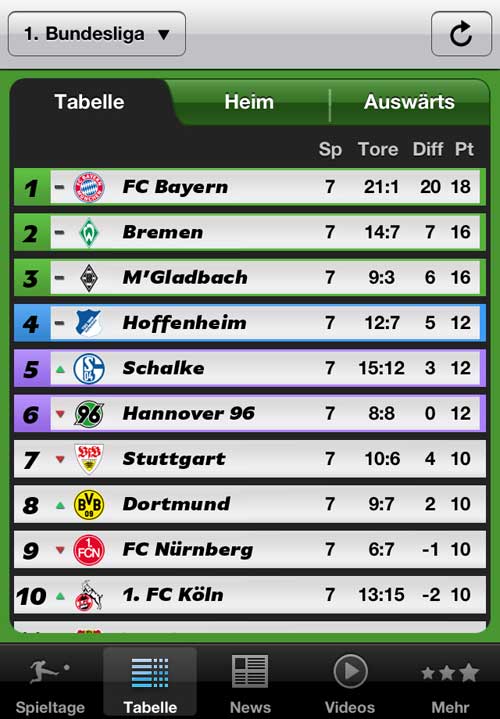
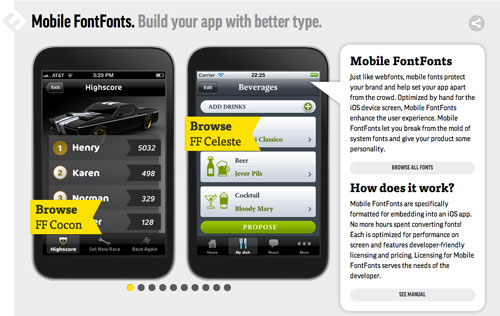
Najaaaa, es gab auch schon Flash auch wenn das AA eher unschön war und es andere Nachteile gab, zumindest brachte das eine gewisse Typovielfalt. Das gibt’s übrigens immer noch und eine große Diskussion diesbzgl. gibt’s immer wenn man das erwähnt ;)
Wenn jetzt letter-spacing noch sauberer (im IE) funktioniert dann bewegen wir uns noch einen guten Schritt weiter Richtung Kapitälchen/Headlines. Aber noch gibt es leider Gründe warum digitale Publikationen anders aussehen als die gedruckten Pendants.
Häää, brauche ich besondere Fonts für eine App? Wenn ich eine App fürs iphone baue kann ich da doch jeden xbeliebigen font reinknallen.
oder gehts jetzt um webapps? aber da gehts doch auch mit @fontface oder???
Gefällt mir !!!!!!
Ina: Es ist eher eine Lizenzfrage als eine technische Frage. Du kannst auch jede Art von Musik in eine App packen, die Frage ist nur: Darfst Du das (Lizenzbedingungen) und wenn ja, was kostet das (mal von selbst gemachter Musik und von selbst gemachten Fonts abgesehen)?
fontshop ist mal wieder vorreiter, find ich gut.
bin gespannt ob es von den entwicklern angenommen wird.
Coole Sache. Auch äußerst faires Preismodell.
Hi Jürgen, dann hab ich echt ne bildungslücke, und mich schon mehrmals schuldig gemacht, ich wusste nicht dass es für apps besondere lizenzen gibt und ich verstehe auch nicht warum. wenn ich für nen kunden ne app schreibe muss ich doch nur eine lizenz haben, die für meinen rechner. auf welchem device das später genutzt wird ist mir doch wurscht oder?
@Ina:
Es kommt darauf an, WAS genutzt wird. Ein Bitmap-Logo oder eine Vektordatei, die mit einem Font erstellt wurde, kannst du beliebig weitergeben.
Aber im Falle der App wird der komplette Font selbst gegebenenfalls millionenfach an die Nutzer der Mobilgeräte ausgeliefert und dort aktiv (also wie ein installierter Font) benutzt. Du gibst also die Software selbst, nicht nur eine damit gemachte Gestaltung weiter. Und das verbietet eine normale Druckschriften-EULA natürlich.
so langsam fühl ich mich wie bei windows mit den ganzen lizenzen.